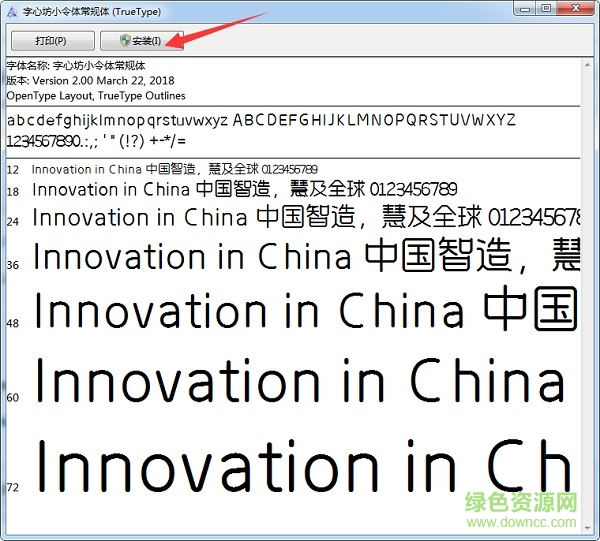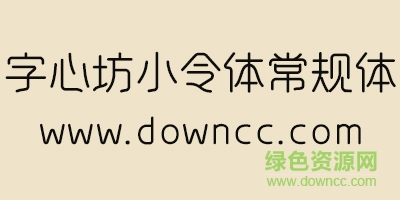
字心坊小令體常規(guī)體是一個免費的字心坊字體應(yīng)用。小編為大家推薦的這款字體是字心坊小令體中的一種,字體規(guī)范,從外觀上看和小篆相似。也是被使用的最多的一款設(shè)計字體!需要的用戶歡迎下載。
字體采用非襯線設(shè)計,字形融合中國小篆與黑體字的特點,取小篆的設(shè)計元素,同時力求精簡,簡化篆書,古為今用,在保證最大化識別度的基礎(chǔ)上,在變化中求得篆書之韻,盡顯古風(fēng)之美。